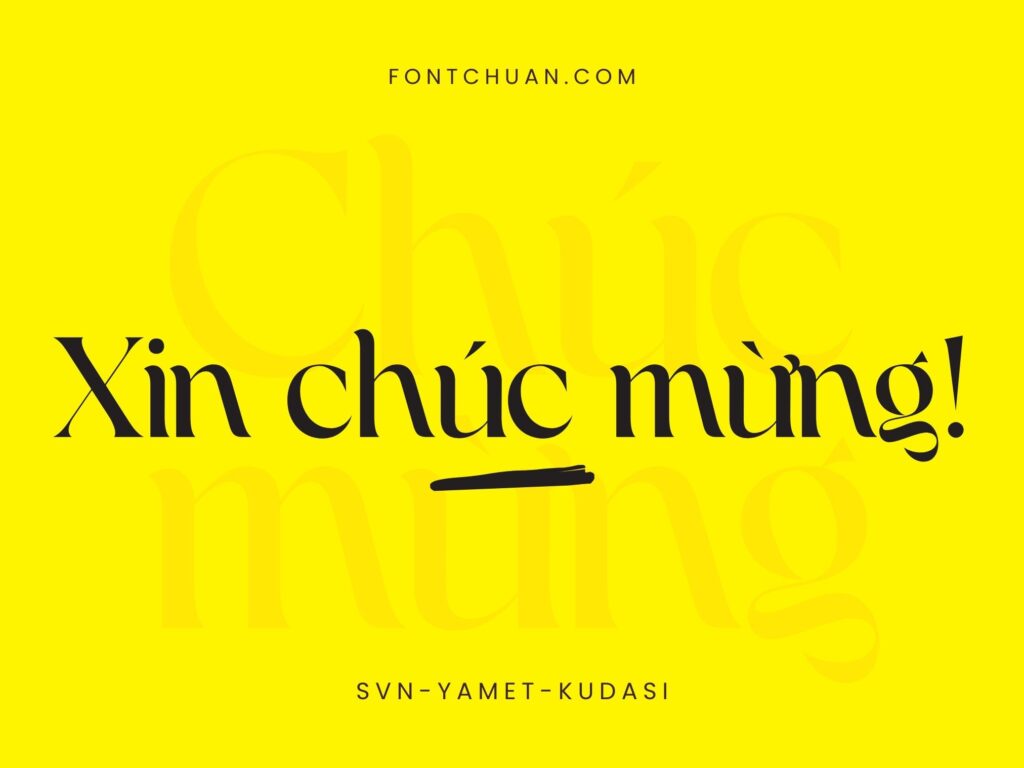
Font SVN Yamet Kudasi Việt Hóa
Tác giả Font: Dean Nugraha
Font SVN Yamet Kudasi là phiên bản Việt hóa của kiểu chữ Yamet Kudasi, được thực hiện bởi Styleno.1 Fonts. Yamet Kudasi thuộc nhóm Font Decorative, mang phong cách kết hợp giữa cổ điển và hiện đại, tạo nên sự độc đáo và thu hút trong thiết kế. Font này hoàn hảo cho việc thiết kế thương hiệu, logo, thiệp chúc mừng, tiêu đề, bao bì sản phẩm và các ấn phẩm quảng cáo khác.
SVN Yamet Kudasi lý tưởng cho các dự án thiết kế yêu cầu sự độc đáo và sáng tạo, như thiết kế logo, thiệp mời, tiêu đề và các ấn phẩm truyền thông. Các ngành nghề như quảng cáo, thiệp cưới và ẩm thực có thể tận dụng font này để tạo điểm nhấn trong thiết kế. Ngoài ra, font cũng thích hợp cho các sự kiện như Tết, Giáng sinh, Valentine và các lễ hội khác.